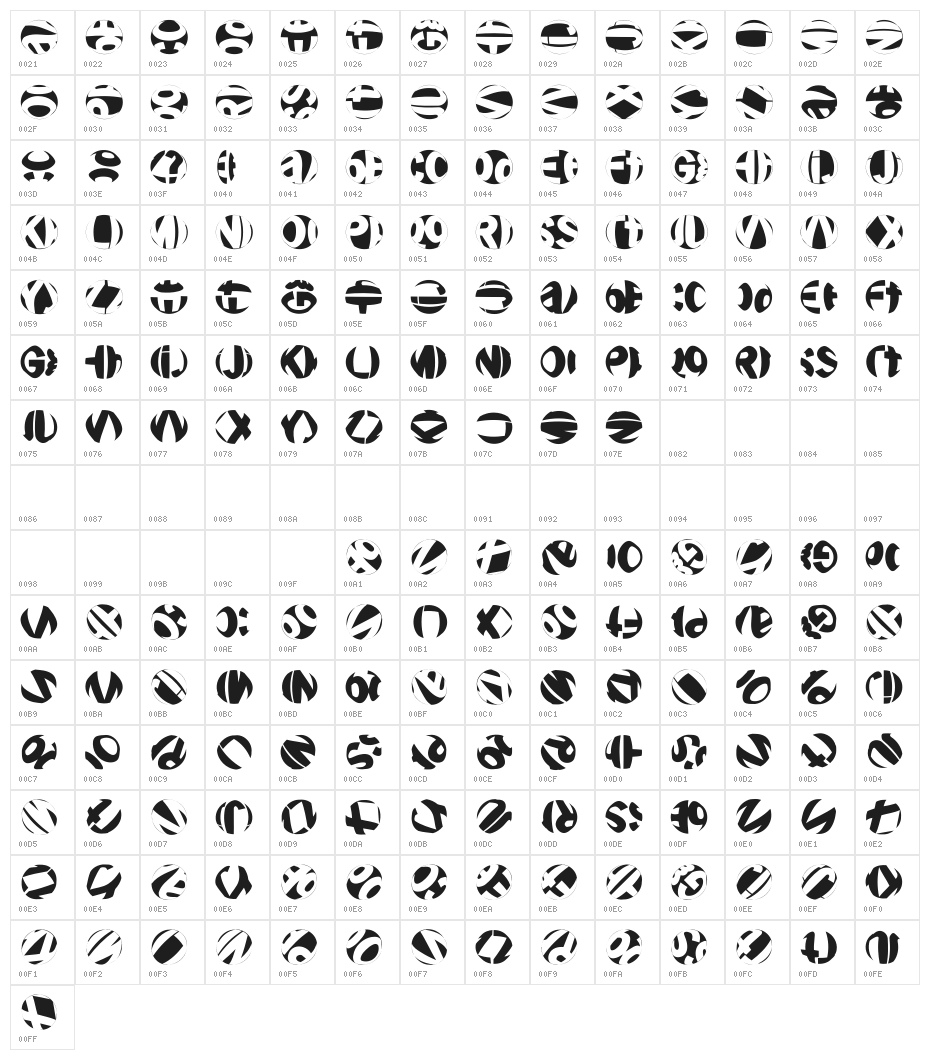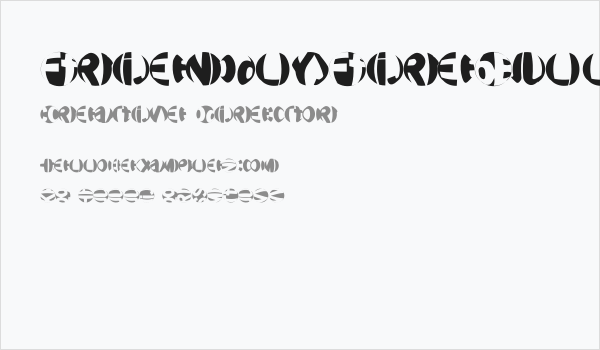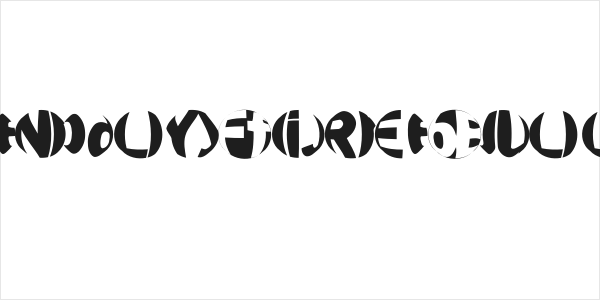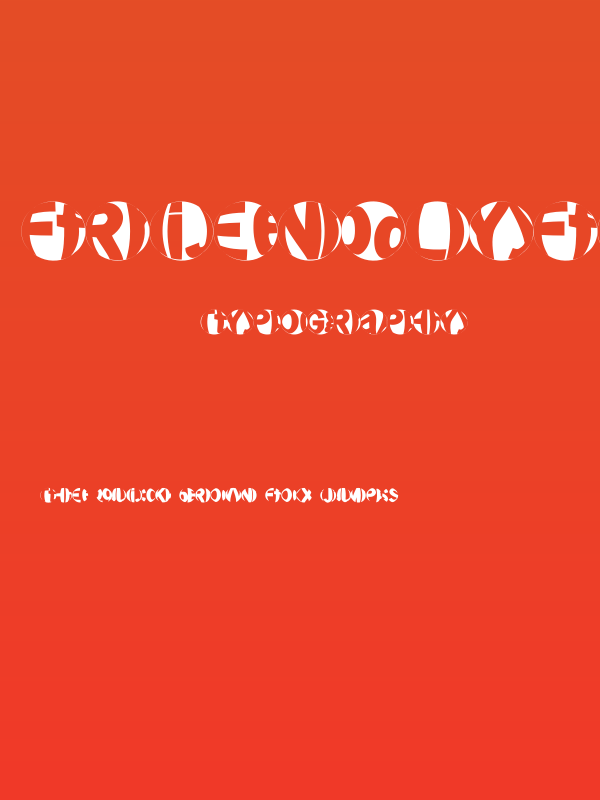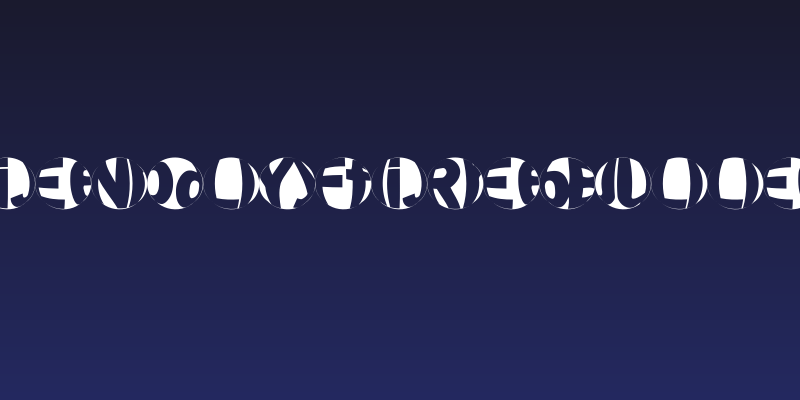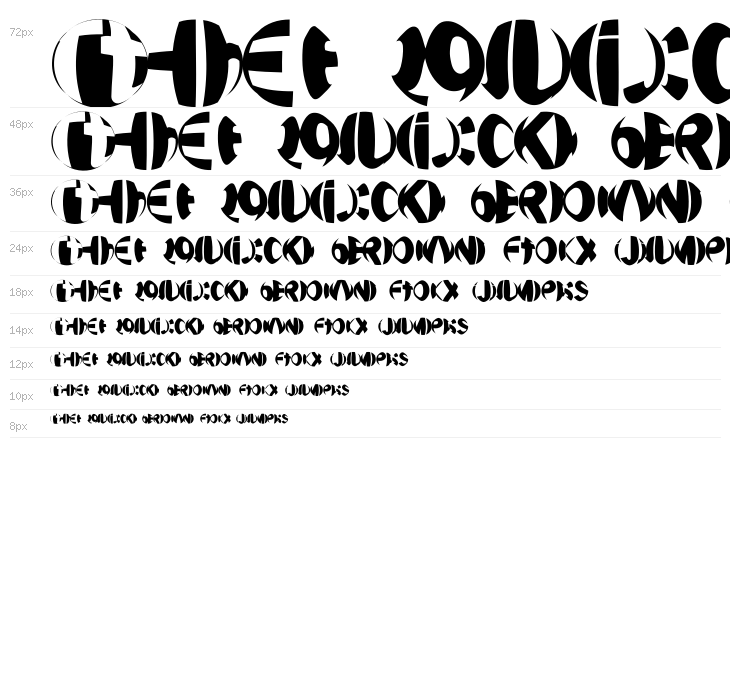
FriendlyFireBullets Font
✎ Futuristic
| श्रेणियाँ | Futuristic |
| चौड़ाई | Condensed |
| कंट्रास्ट | High |
| समग्र शैली | Modern, Artistic |
| उपयोग का मामला | Headlines, Logos, Posters |
| सुझाए गए प्रोजेक्ट | Ideal for album covers, posters, branding, and any project needing a bold, artistic statement. |